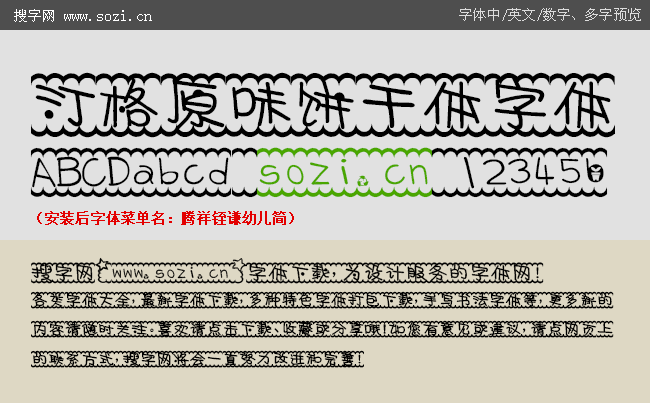
汀格原味餅干體字體
搜字網(wǎng)給大家提供一款很有趣的手機中文字體下載。字體名字叫汀格原味餅干體字體,這款手機字體是在騰祥铚謙幼兒簡體字體的外面加上了卡通邊框圖案。騰祥铚謙幼兒簡體為POP手繪字體。由資深硬筆書法家、手繪pop創(chuàng)意設(shè)計師高铚謙手繪完成原字稿。字里行間充滿童真稚趣,彰顯活潑靈動的個性。特別適合喜歡手機字體個性一些的朋友在手機上安裝使用。